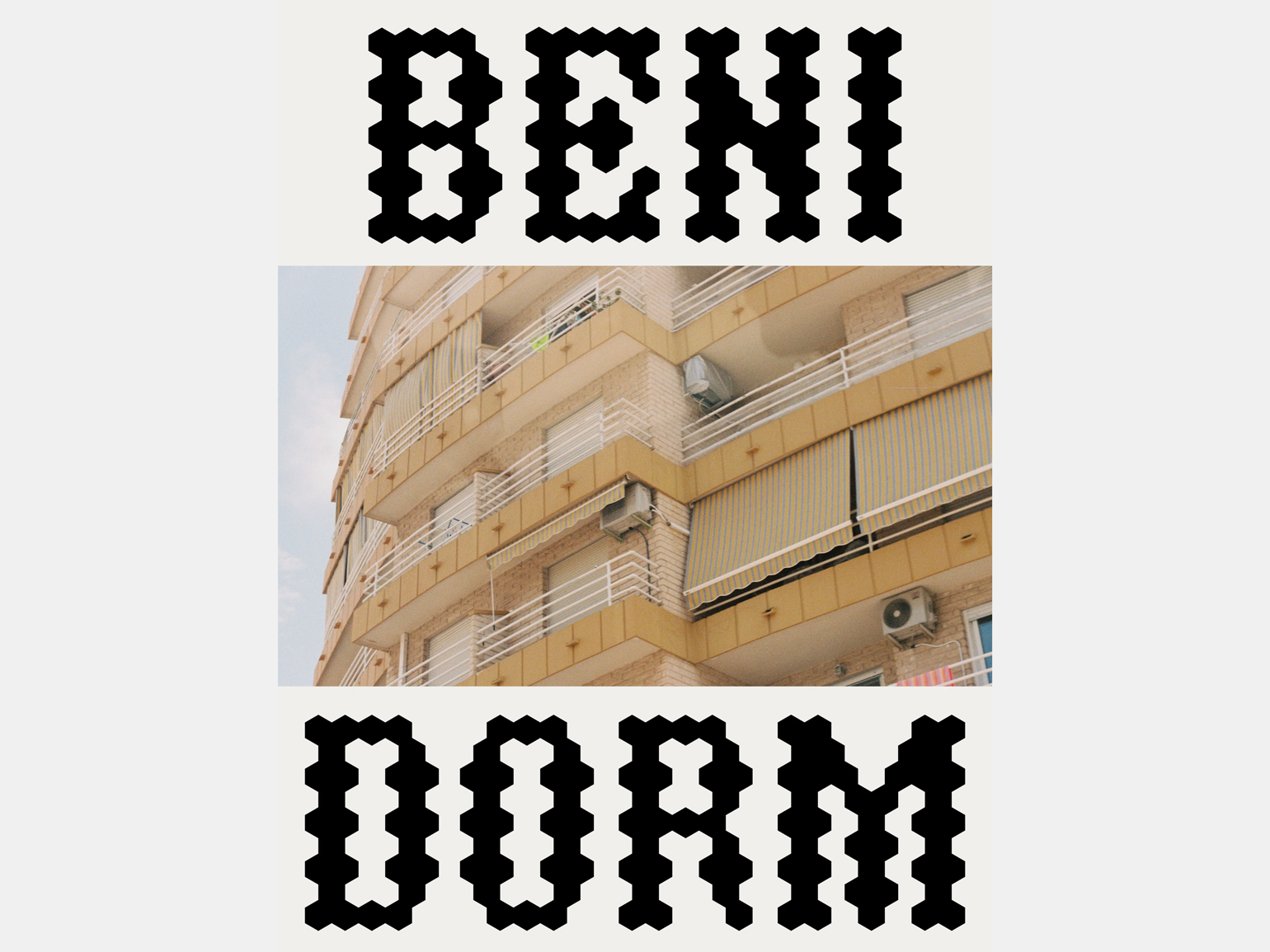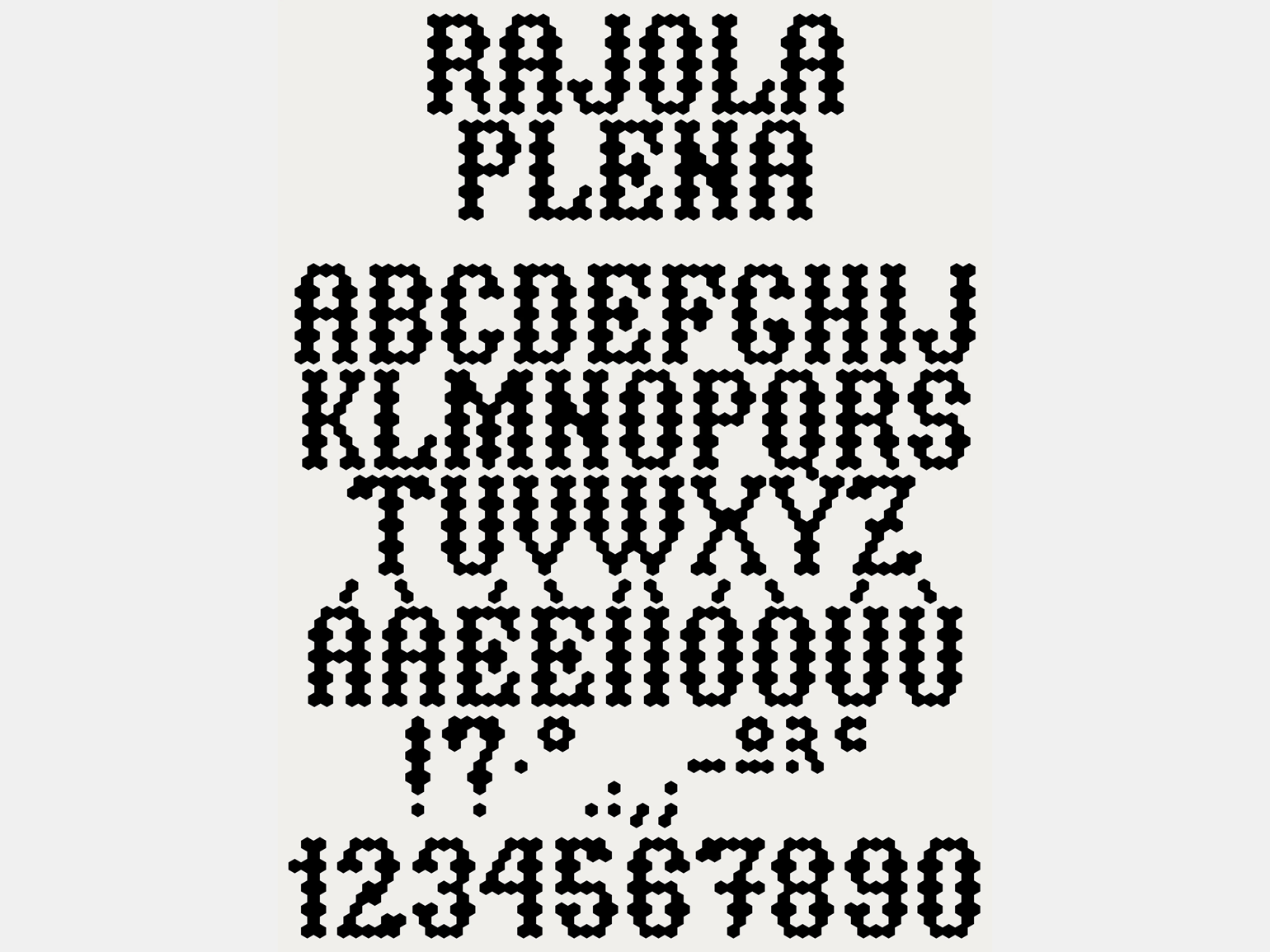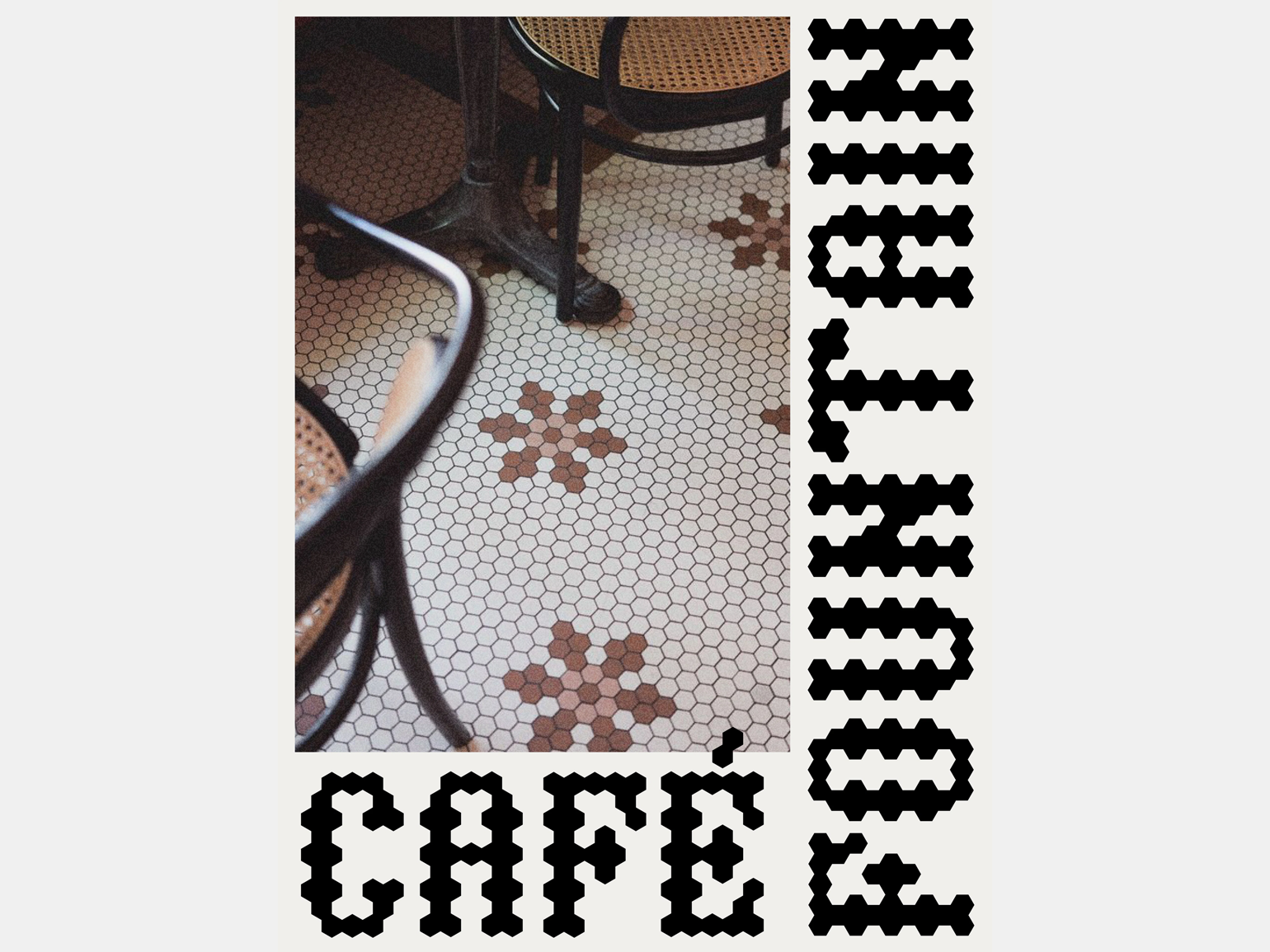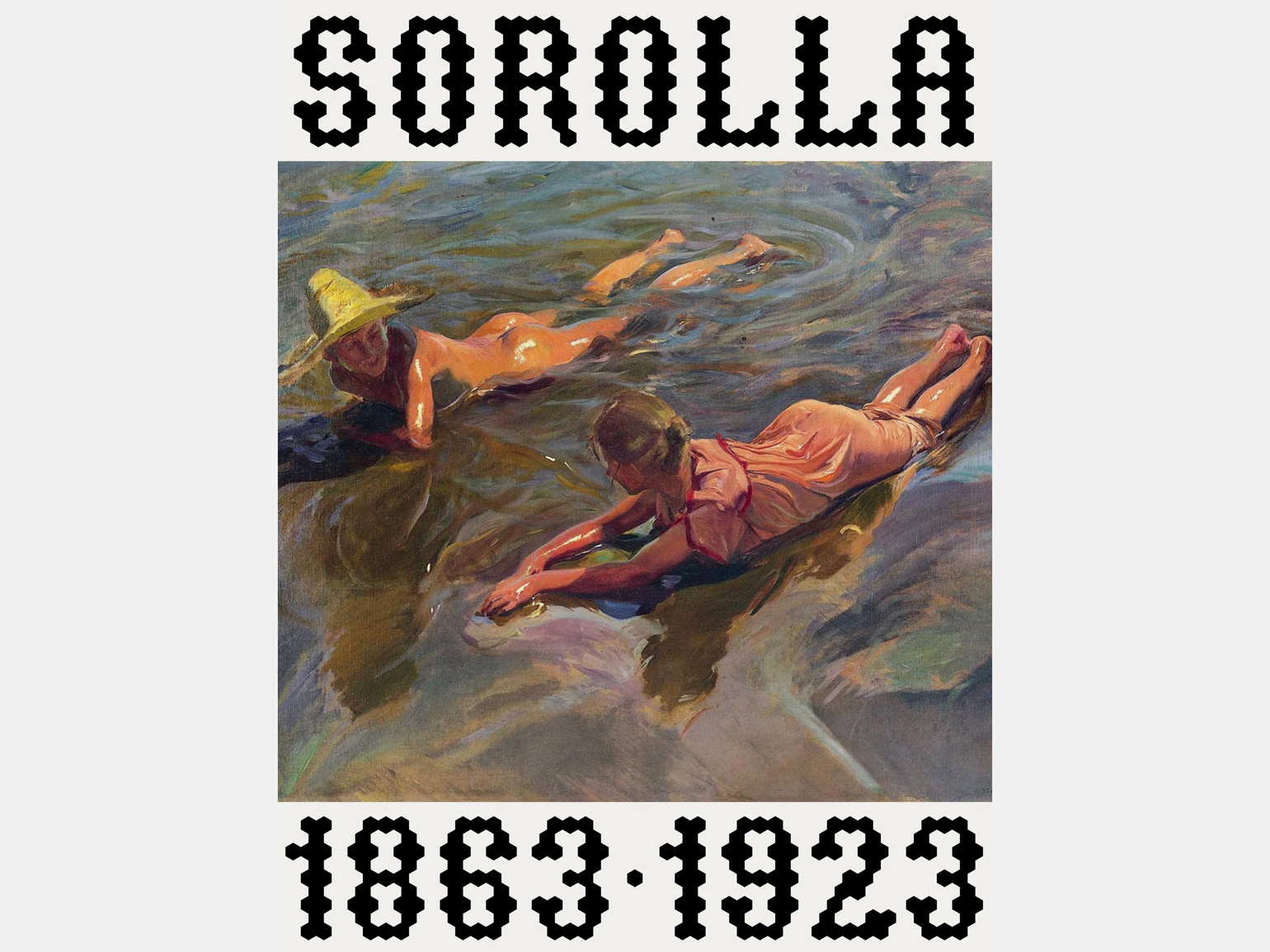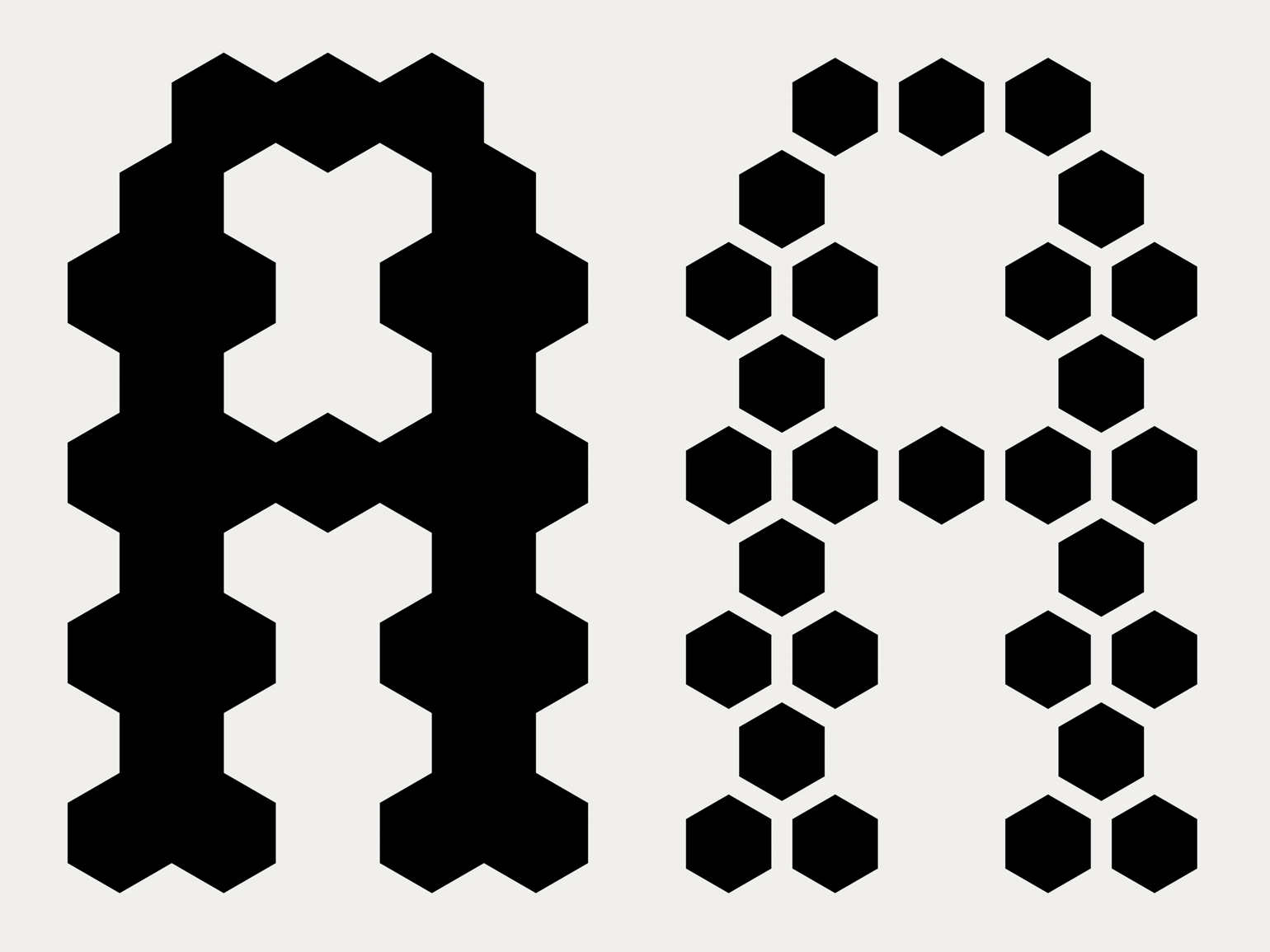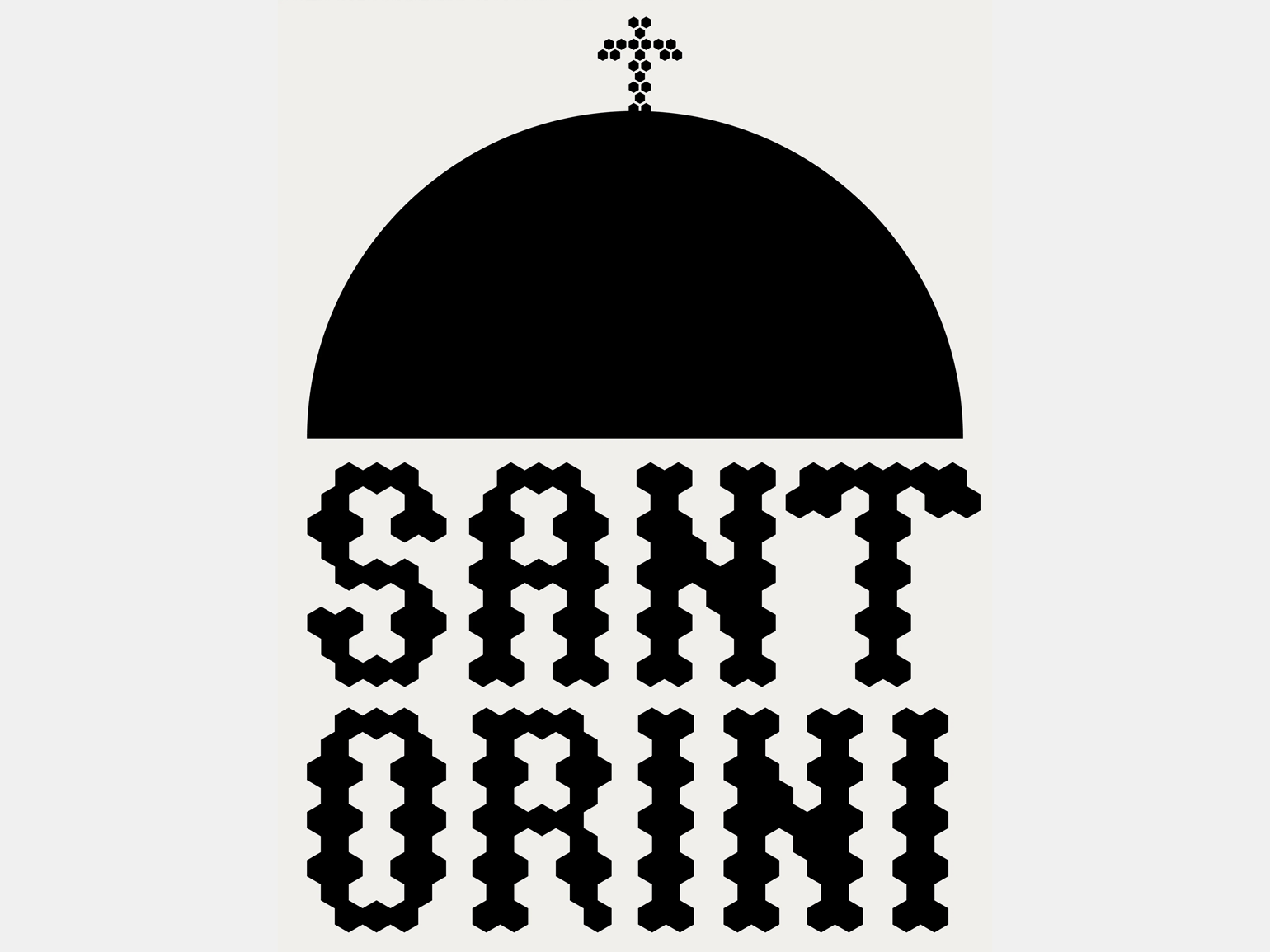
Дизайнеры сделали шрифт, вдохновившись средиземноморской плиткой
Он представлен в двух вариантах.
Мы уже писали о том, как дизайнеры создают проекты, напоминающие о городской среде. Сейчас валенсийская студия errorerror.studio® сделала акцидентный шрифт Rajola®, напоминающий, возможно, о главной особенности средиземноморского интерьера.
Средиземноморский стиль ассоциируется с белыми зданиями, длинными заборами, усеянными цветами, и кафельной плиткой внутри дома — и бетонной снаружи. Такая поверхность хорошо охлаждает в жару, а ещё можно варьировать её формы и цвета.
Шрифт Rajola®
Шрифт Rajola® зародился в другом проекте, когда дизайнерам поручили создать плакат со словом «Валенсия». В студии хотели, чтобы надпись состояла из чего-то, что напрямую связано с Валенсией. Первоначально склонялись к цветам, потому что символ города — гвоздика. Но они поняли, что такая задача выйдет за рамки бюджета, и стали искать что-то более графичное. После многочасовых исследований они остановились на кафельной плитке: благодаря своим прямым краям она похожа на пиксель и легко вписывается в сетку.
Шрифт Rajola®
Чтобы сделать что-то, что выглядит как «старое, классическое и традиционное», дизайнеры создали орнаментальный шрифт с угловатыми засечками. После плаката errorerror.studio® решили не останавливаться на надписи и создали полноценный шрифт. У него две вариации: в одной версии шрифта плитки сливаются воедино, оставляя только намёк на мозаичную композицию, а в другой их форма отчётливо видна и это похоже на пиксельное изображение.
Шрифт Rajola®
Rajola® — это дисплейный шрифт, который лучше всего использовать в умеренном количестве для дизайна плакатов и брендинга. Студия показала это с помощью плакатов, в которых объединила буквы со своими аналоговыми фотографиями средиземноморской архитектуры и интерьеров.
Шрифт Rajola®